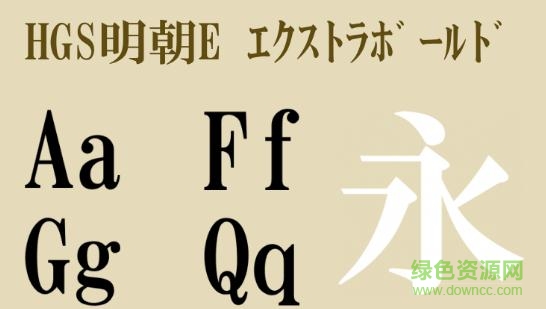
hgsminchoe字體是一款筆畫硬挺橫細豎粗的日本明朝字體,這款字體美觀端莊,起落筆流暢自然,非常適合用在正文排版中,整體效果非常棒,喜歡日文字體的朋友快來免費下載吧!
在電腦漢字字體設計的最初,日本率先設計了明朝體,后來傳入韓國、中國臺灣,所以兩地也有明朝體的叫法。時至今日,由于中日兩國文字簡化方案的不同,兩國文字已經有了很大的不同,明朝體也就徹底成為一種外文字體了。